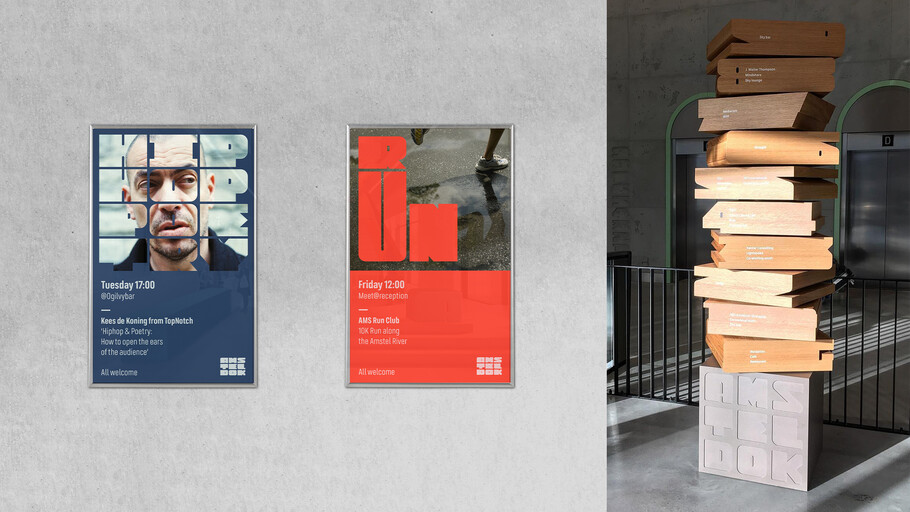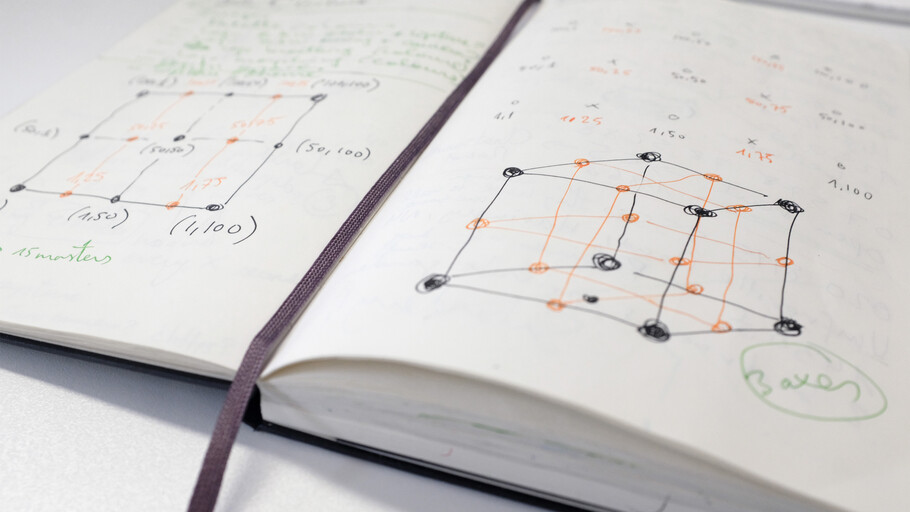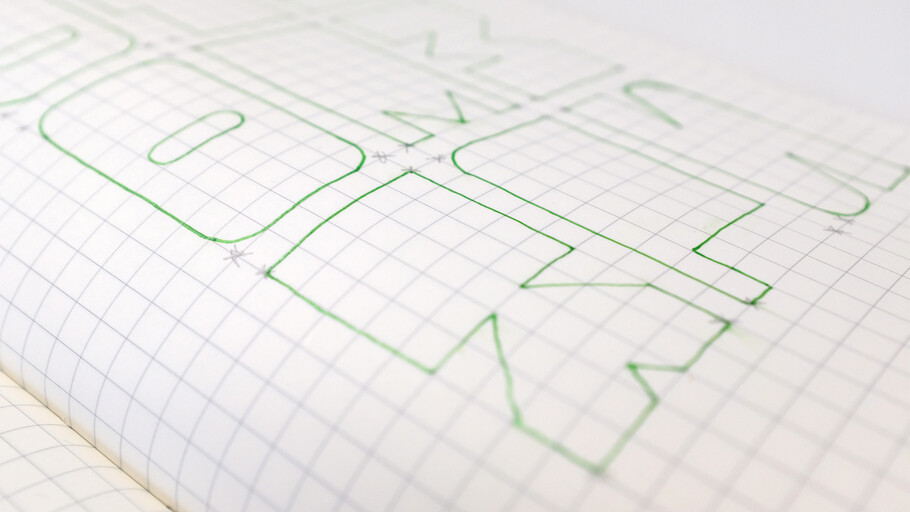
Amsteldok.
O primeiro logotipo de fonte variável do mundo para a WPP.
Em uma abordagem inovadora e dinâmica ao novo formato de fonte variável, a Fontsmith (agora parte do Monotype Studio) e a agência de marca holandesa VBAT criaram uma fonte de logotipo responsiva para o novo campus da WPP em Amsterdã – um logotipo que muda de acordo com a interação e o tempo, à medida que as pessoas se movem pelo espaço, alterando também o formato de suas letras.
O formato do logotipo se transforma com diferentes gestos humanos; enquanto sua paleta de cores se altera suavemente de acordo com a hora do dia e da noite – tudo refletindo o conceito criativo do prédio e daqueles que “respiram” criatividade nesse espaço.
Resumo.
A equipe foi contratada pela VBAT no final de 2018 para ajustar um logotipo modular que se inspirava em influências do design holandês clássico do século 20 – moderno, experimental e ousado. Juntos, questionamos se havia oportunidade para desenvolver uma tipografia interativa e responsiva, uma obra de arte que mostrasse a flexibilidade modular da fonte. As fontes variáveis são o próximo grande avanço no design de fonte e, embora tenha havido muita experimentação com pesos e larguras adaptativos, queríamos ir além e criar algo verdadeiramente responsivo e não convencional. Como designers, queríamos trazer uma nova abordagem para uma nova tecnologia, criar uma fonte prática com propriedades experimentais, algo nunca antes visto.
Havia uma visão clara de que a fonte do logotipo poderia ser levada além de um logotipo estático, reagindo à interação do usuário, tornando-se um sistema de wayfinding orientação em todo o edifício.
Abordagem.
O logotipo foi criado inicialmente experimentando com as proporções das letras, mantendo a essência principal da marca. Várias versões finais se tornaram “fontes mestras” que podiam ser interpoladas e combinadas para criar um grande número de novas variações. Em seguida, trabalhamos com o desenvolvedor Carlos Sánchez para criar um software responsivo que animaria o eixo de design das fontes do logotipo na tela de acordo com os movimentos das pessoas.
Queríamos que o trabalho incorporasse o esquema de cores da marca, mas também queríamos criar outra função, um esquema de cores em estado ocioso que permitisse que o logotipo refletisse uma sensação de tempo. Criamos um esquema de cores que se adapta a cada 40 minutos, seguindo a jornada do sol ao longo do dia – mudando de tons de azul à noite para tons amarelos durante o dia.
Resultado.
As letras de Amsteldok formam um logotipo tipográfico fluido e mutante que responde à interação do usuário por meio de uma câmera de mapeamento de calor. Portanto, à medida que as pessoas passam pela área de recepção do Amsteldok, a fonte também se adapta, permitindo que todos se divirtam com o logotipo e dando vida à identidade para criar uma experiência de marca mais física e imersiva.
A VBAT está atualmente desenvolvendo um conjunto de princípios de identidade visual para ser usado em todas as localizações globais dos campi da WPP, usando a família de tipos de letras família de fontes FS Industrie da Fontsmith.
“O logotipo é uma entidade viva: está sempre ‘respirando’ (mesmo em repouso como nós); respondendo às pessoas e movimentos em tempo real. As letras reagem ao ambiente e entre si dentro das limitações de sua grade, mantendo ainda consistência como uma marca distinta, reconhecível e lúdica.” — Diretor criativo de fonte, Pedro Arilla.